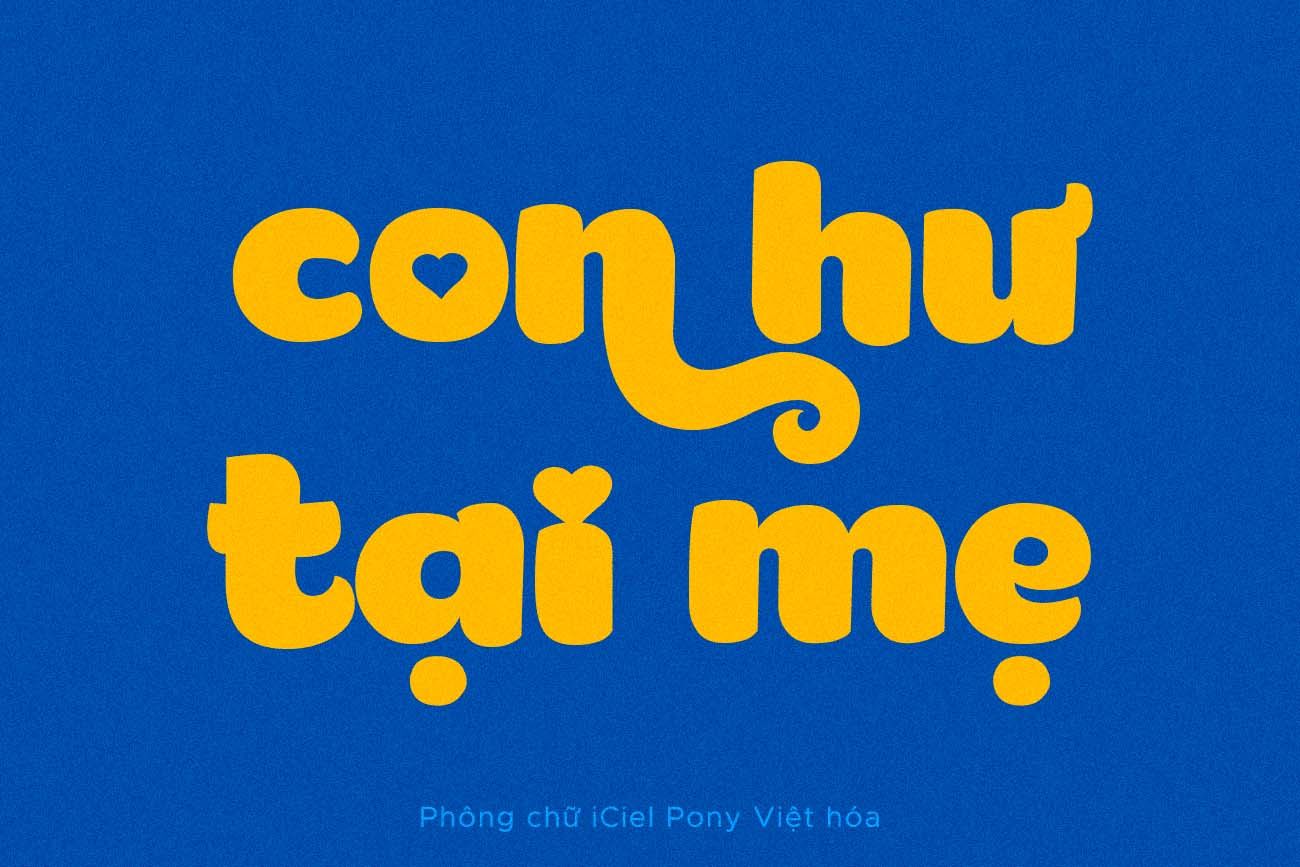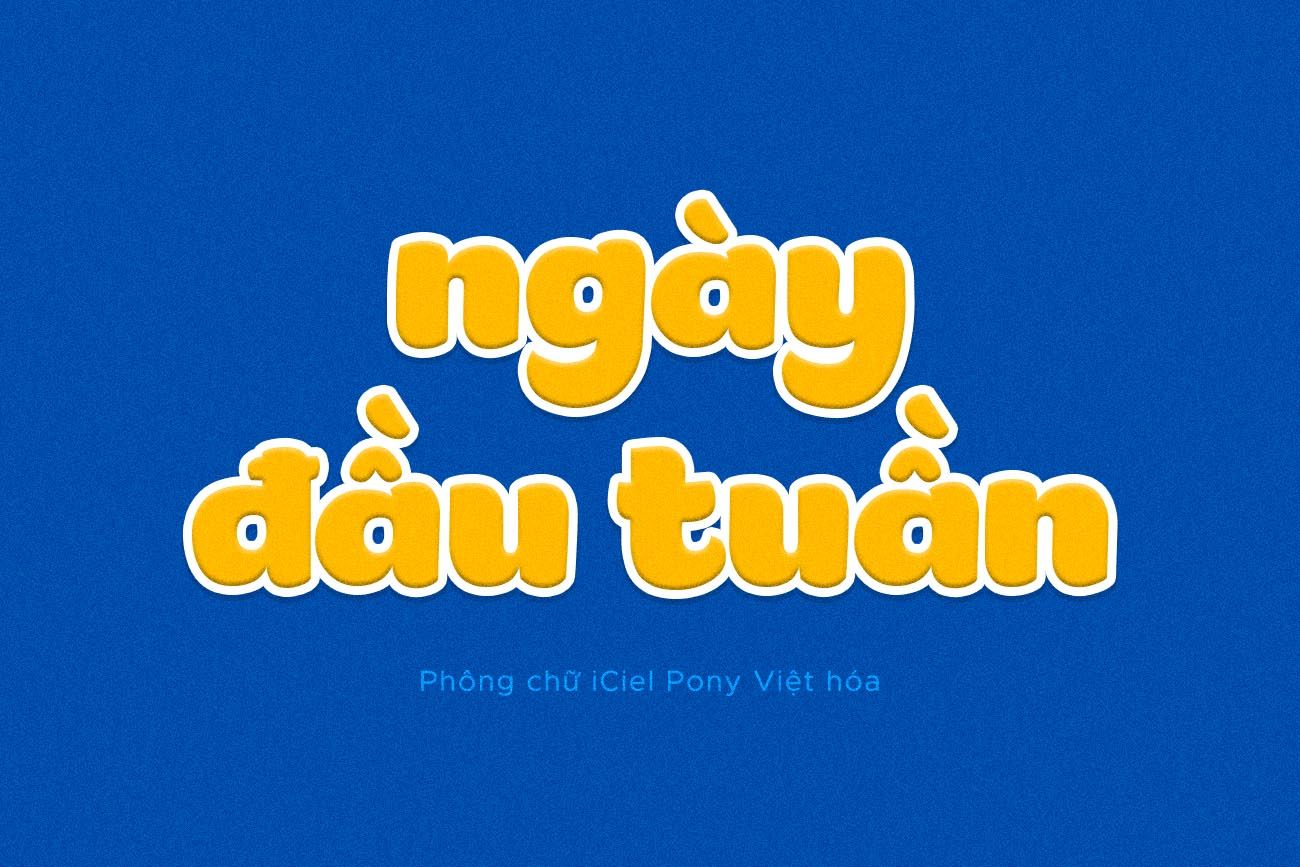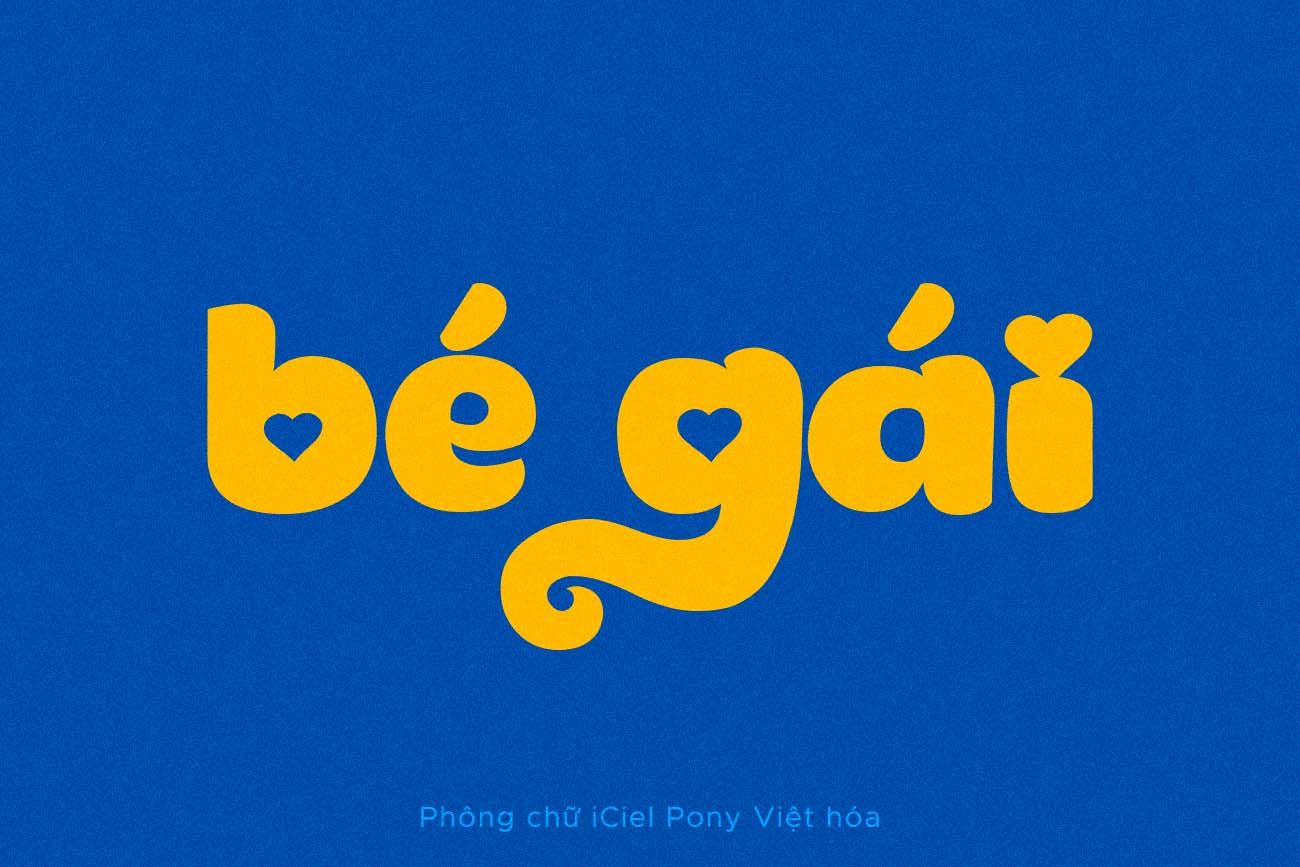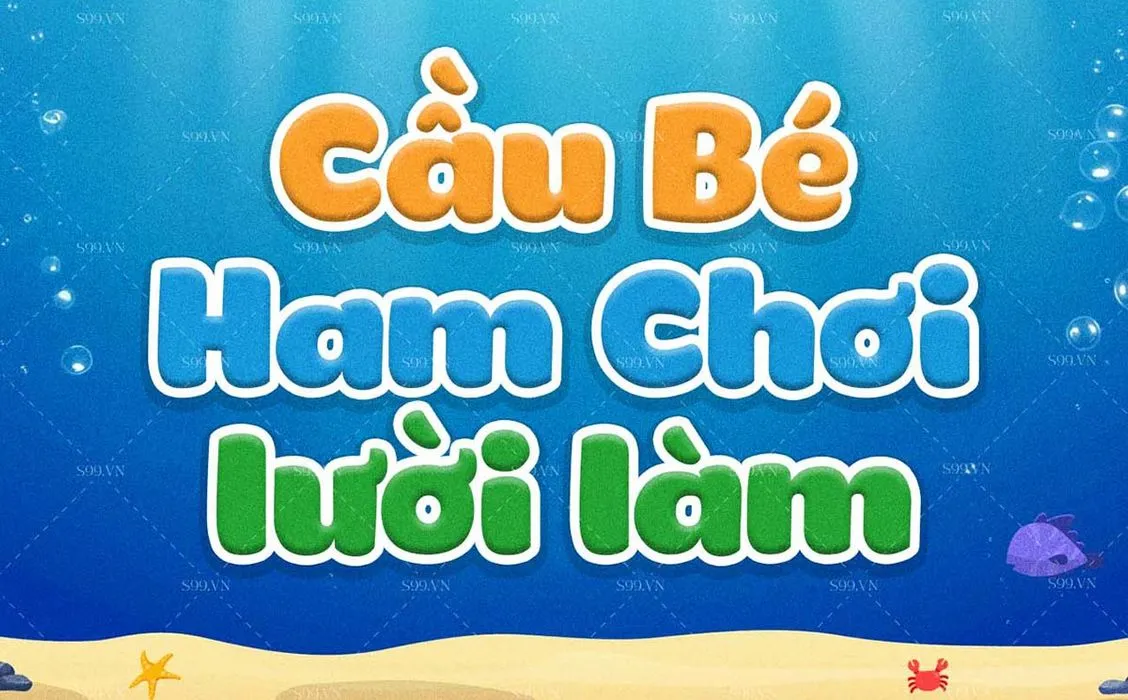
iCiel Pony là một trong những bộ font chữ tròn nổi bật nhất do nhóm thiết kế iCiel phát triển tại Việt Nam. Không giống như nhiều bộ font Việt hóa từ nước ngoài, iCiel Pony được sáng tạo nguyên bản, mang phong cách riêng biệt với các đường nét bo tròn, mập mạp và mềm mại. Chính sự tròn trịa ấy tạo nên cảm giác vui nhộn, dễ thương và gần gũi, rất thích hợp cho những thiết kế cần sự thân thiện, đáng yêu.
Font chữ này thường được gọi là font chữ béo tròn hoặc font chữ tròn mập, bởi hình dáng chữ cái đầy đặn, gợi cảm giác bông xốp như những chiếc bánh ngọt. Với nét chữ dày, tròn, iCiel Pony dễ dàng thu hút sự chú ý ngay từ cái nhìn đầu tiên, đặc biệt khi sử dụng trong các ấn phẩm dành cho trẻ em như poster, bìa truyện tranh, đồ chơi, nhãn dán hoặc các sản phẩm học tập.
Điểm mạnh của iCiel Pony là hỗ trợ đầy đủ tiếng Việt, bao gồm tất cả ký tự có dấu. Điều này giúp người dùng dễ dàng ứng dụng font vào tiêu đề, banner, logo hoặc các sản phẩm in ấn mà không lo bị lỗi ký tự. Nhờ sự Việt hóa chuẩn chỉnh từ chính nhóm tác giả gốc, font giữ được sự cân bằng giữa nét thẩm mỹ và tính ứng dụng.
Trong thiết kế hiện đại, iCiel Pony còn được ưa chuộng trong các dự án branding cần sự trẻ trung và gần gũi. Chẳng hạn, một thương hiệu đồ ăn vặt, quán cà phê cho giới trẻ hay cửa hàng đồ chơi đều có thể dùng font này để xây dựng hình ảnh thân thiện và dễ nhớ.
Nếu bạn đang tìm kiếm một font chữ cute, tròn mập và đáng yêu, iCiel Pony chắc chắn là lựa chọn hoàn hảo. Đây là font không chỉ mang lại hiệu ứng thị giác dễ chịu mà còn truyền tải sự vui tươi, phù hợp với nhiều phong cách thiết kế trẻ trung, năng động.